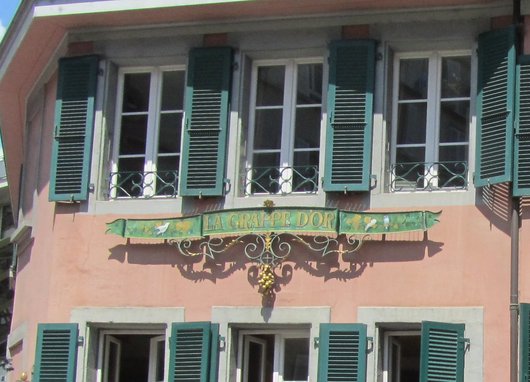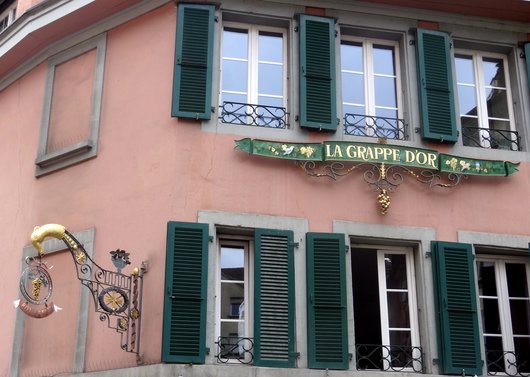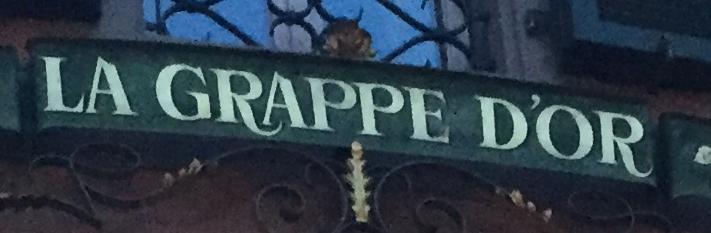
Ich suche vergeblich nach dieser Schrift, komme einfach nicht weiter. Hat vielleicht jemand von euch Tipps oder Hinweise?
Ich habe das Schild in der Schweiz, Lausanne fotografiert. Das Restaurant (und vielleicht auch die Schrift?) stammt von 1954.
Das sieht doch sehr handgemalt aus, würde auch zur Zeit passen – das P und R sind schon sehr unüblich ...
Ähnlich wäre vielleicht:
Das wurde wahrscheinlich individuell von einem Designer gestaltet, wie Schnitzel schon gesagt hat. Vor allem das R sieht sehr auffällig aus, was schon ein Hinweis dafür wäre, dass dieses Logo auf keiner Satzschrift basiert.
@Schnitzel: Die Tiffany Heavy passt aber nicht wirklich; schon aufgrund der Dicke und der Formen.
Mir fällt spontan jedoch auch keine alternative Satzschrift ein :-?.
die tiffany gibts auch feiner aber das schild ist sicherlich handgemalt, anscheind wurde es auch mal erneuert und der 'schwanz' vom alten schild übernommen.
das R sieht auch eher so aus, als hätte man das P genommen und um den 'schwanz' erweitert.